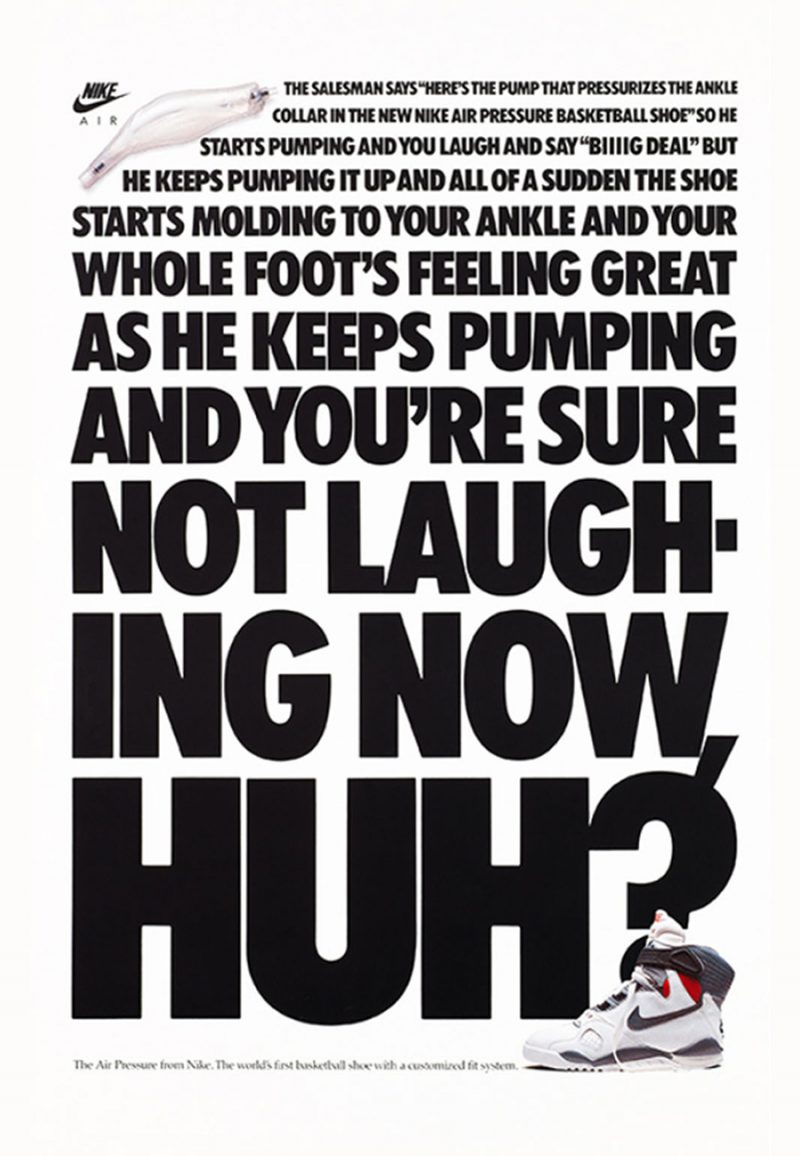
Tipografía de palo seco y dibujo geométrico
En el año 1927, en un contexto histórico en el que Alemania reivindicaba la modernidad, la Bauhaus emergía como centro de creación y las imprentas y fundiciones del país se debatían entre las tipografías góticas y las romanas, Paul Renner presentó una nueva tipografía para la fundición Bauer, a la que llamarían Futura y que conquistaría al mundo.
La Futura es una fuente tipográfica de palo seco, basada en formas geométricas básicas como el cuadrado, el círculo o el triángulo. Dispone de una amplia gama de cuerpos y tipos, así como de sus versiones normal, ancha y estrecha. Esta versatilidad, junto con el acierto en su dibujo, posibilitó su rápida acogida y gran popularidad durante los años treinta del siglo XX.
Su éxito queda plasmado en la gran cantidad de publicaciones, cubiertas, carteles y logos en los que ha sido utilizada, y a pesar de la introducción de nuevas tipografías de palo seco como la Helvetica, de Max Miedinger o la Univers, de Adrian Frutiger, lanzadas durante la década de los años cincuenta, la Futura ha conseguido erigirse como uno de los grandes clásicos de la historia universal de la tipografía.